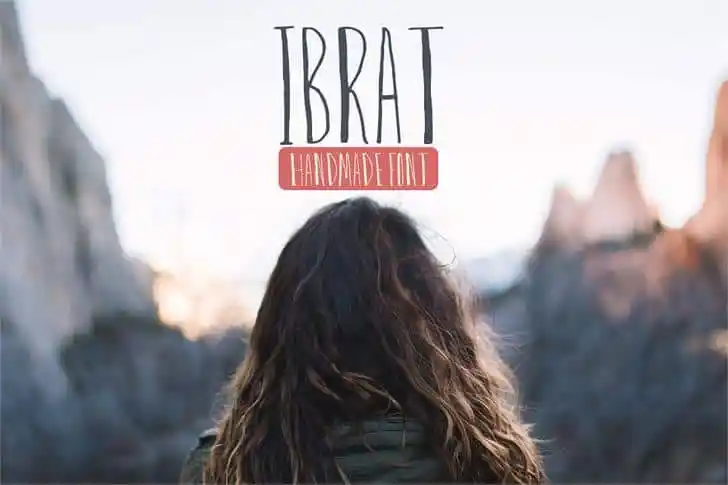
Ibrat Font – Download Grátis
Introduzimos a Ibrat, uma fonte criada à mão com traços rústicos e muita personalidade. Este é um tipo de calligrafia que foi meticulosamente feito usando um pincel para escrever, garantindo o look genuíno e autêntico. A característica mais intrigante da Ibrat está em cada uma das letras do alfabeto – todas foram criadas com a delicadeza e cuidado de um artista real. Este é um recurso que oferece aos designers a chance de adicionar um toque único, elegante e vibrante às suas criações digitais. Escolhida por designers apaixonados por arte, Ibrat é uma excelente fonte para aqueles que buscam uma maneira única de incorporar elementos artísticos em seus projetos. Seja para agradecer, celebrar ou simplesmente desfrutar do belo da linguagem, esta fonte é certamente um elemento diferenciador. CriativoTacos, o criador desta fonte, destaca-se pela sua habilidade de capturar o espírito humano na arte das letras. Não é apenas uma fonte, mas uma jornada visual que remete diretamente para a essência da escrita.